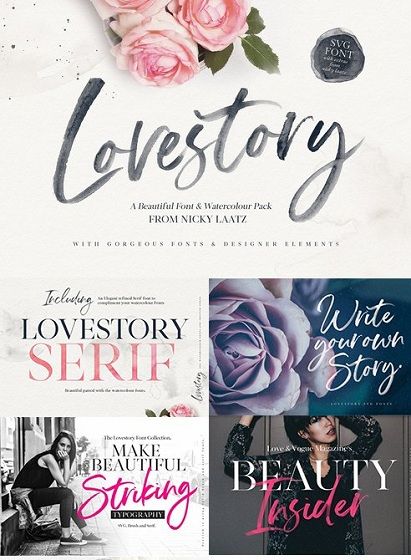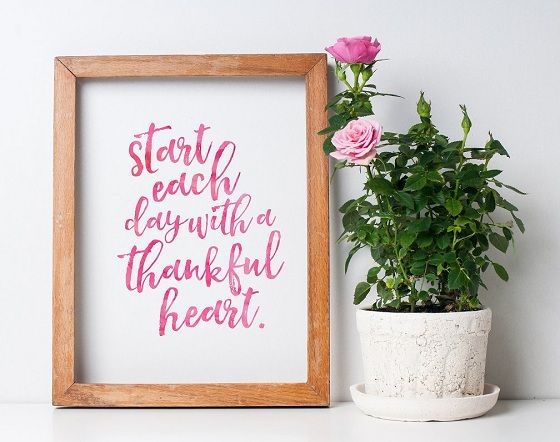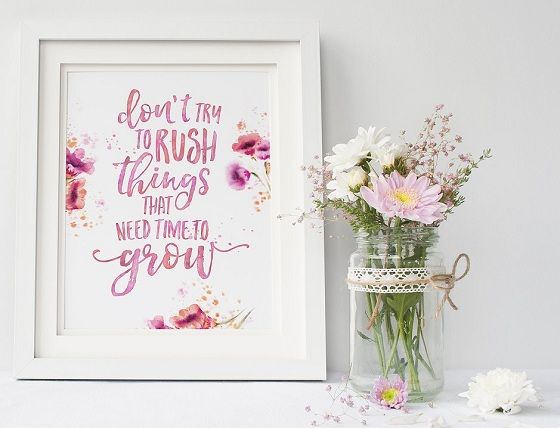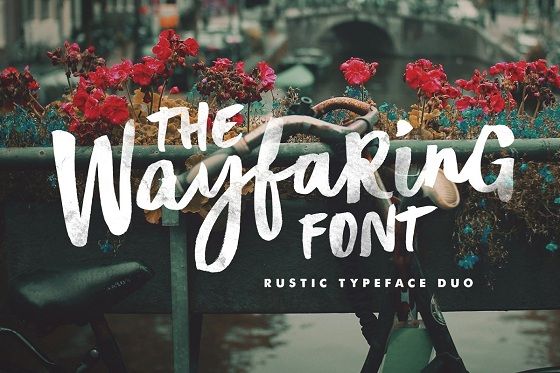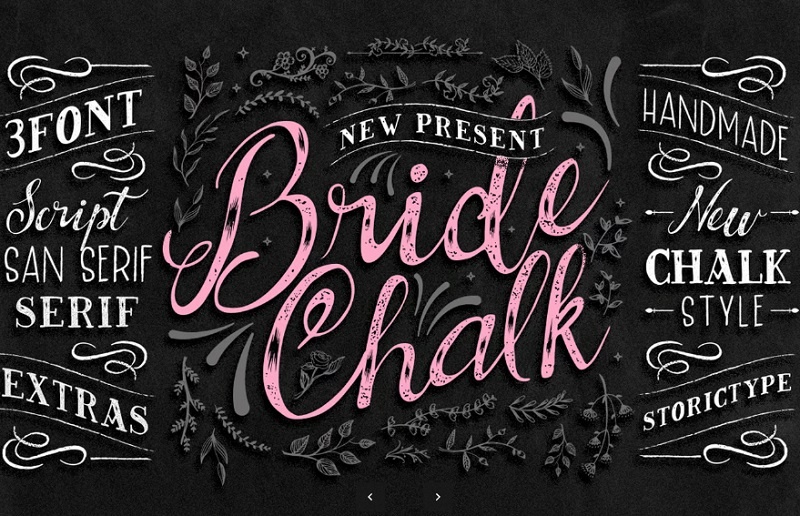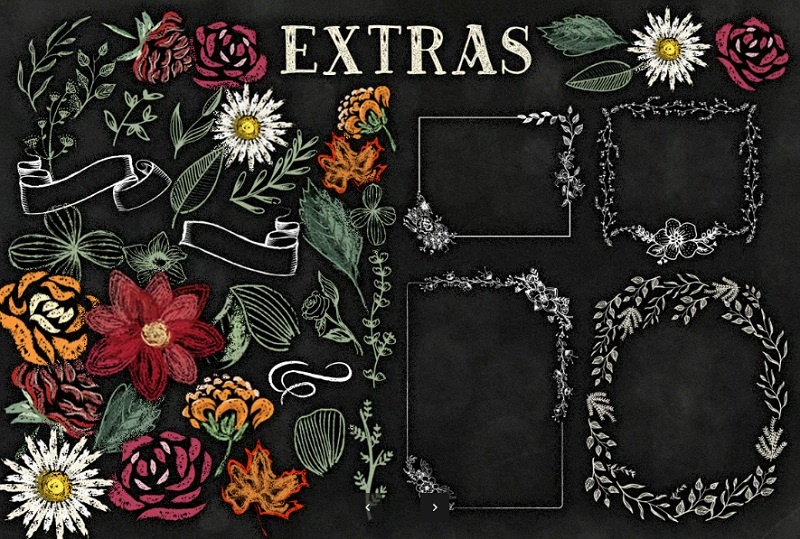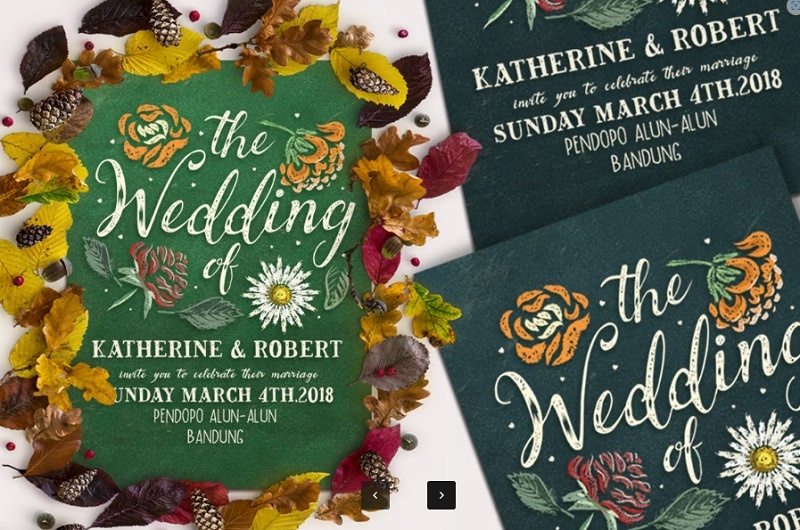
دانلود مجموعه فونت برای عروسی
دانلود فونت برای عروسی
دانلود مجموعه فونت های عروسی
wedding lovely font collection نام این پکیج فونت عروسی می باشد که در بیش از 3 مجموعه مختلف عرضه شده است. شما می توانید برای استفاده در طراحی های مختلف مخصوصا طراحی های کارت دعوت، عکس ها، آلبوم و سایر طراحی های دیگر با موضوع عروسی، نامزدی و عاشقانه از این مجموعه فونت انگلیسی استفاده نمایید.
ویژگی های فونت انگلیسی عروسی از جی اف ایکس دانلود
✅ شامل 4 مجموعه از فونت انگلیسی عروسی